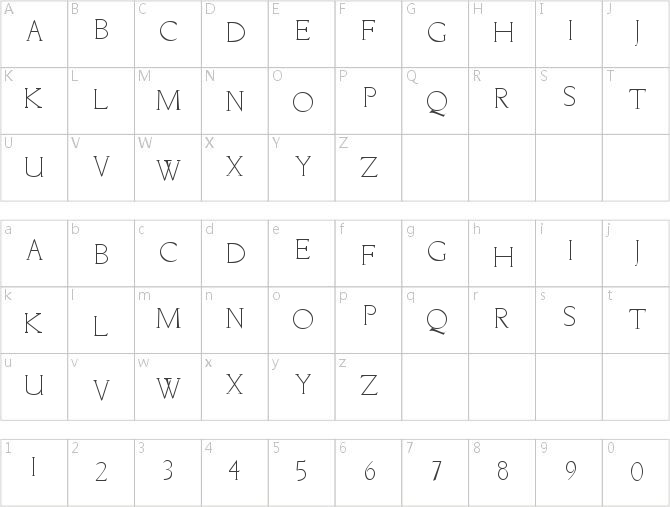
字体名称: Lichtne
Lichtner-Regular
Lichtner-Regular介绍
Lichtner-Regular字体字库是一款让人赏心悦目、百看不厌的英文字体,适合各类广告和产品包装设计应用,字体大小0.03MB,格式为ttf字体,上传用户是多拉MO,作者/版权方为未知
Lichtner-Regular效果图